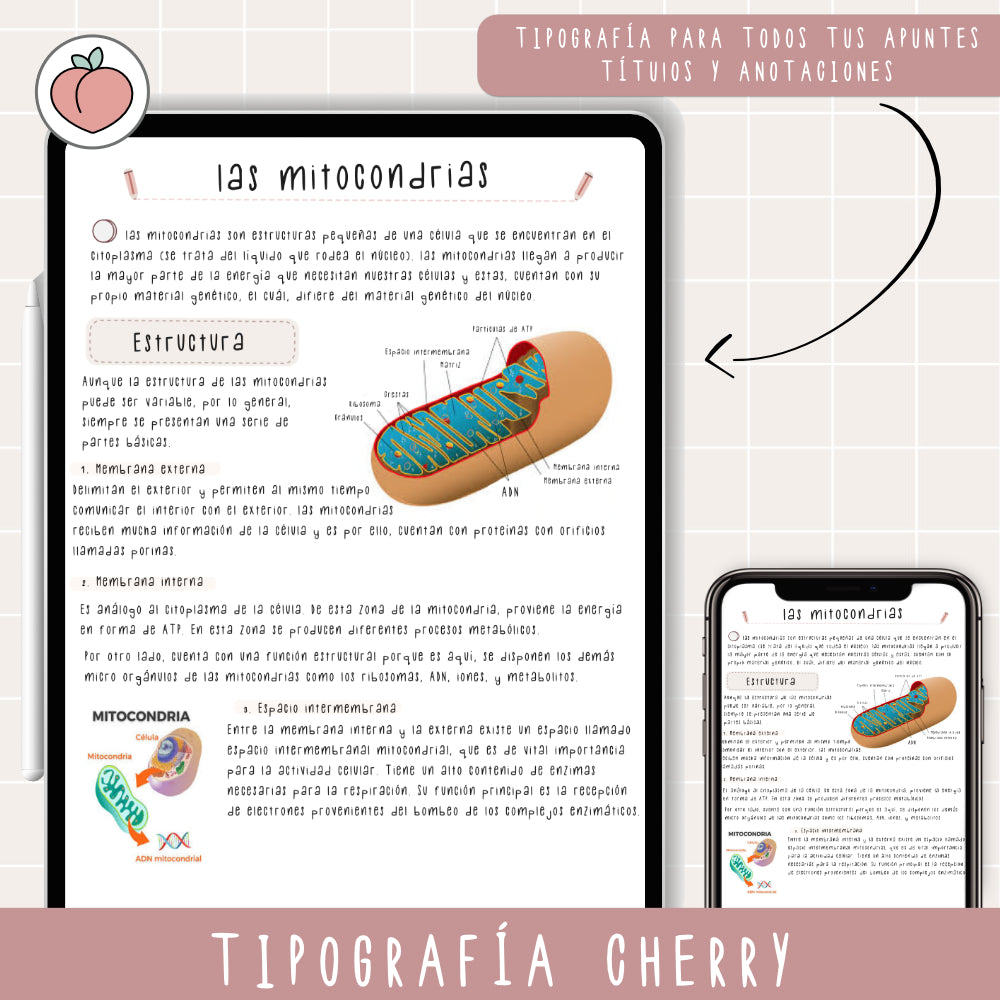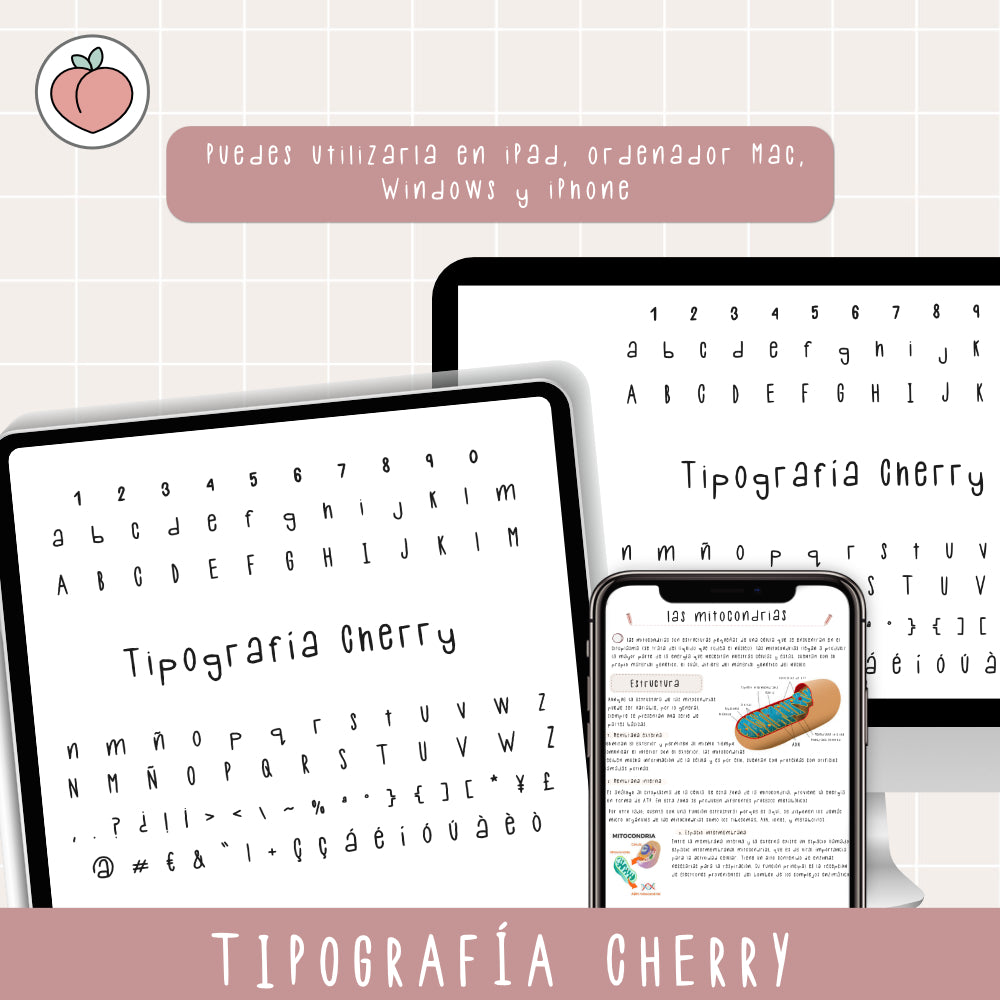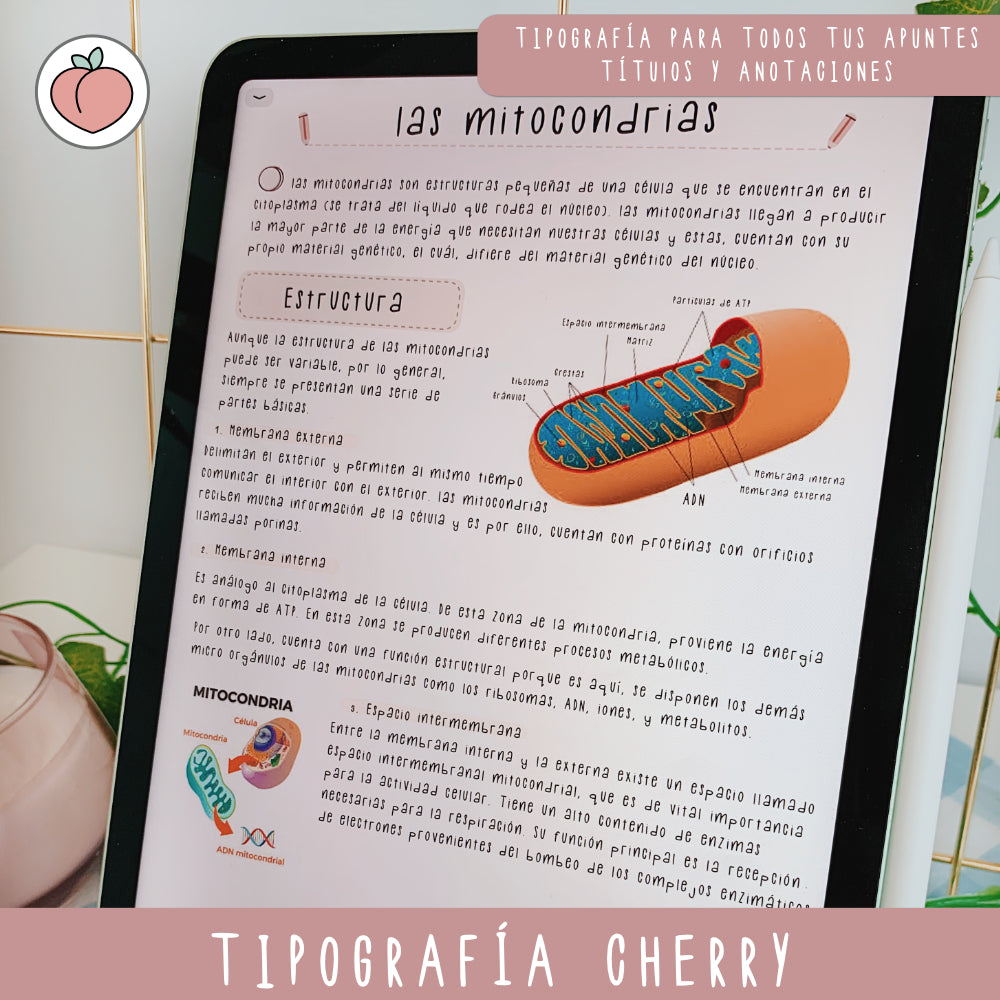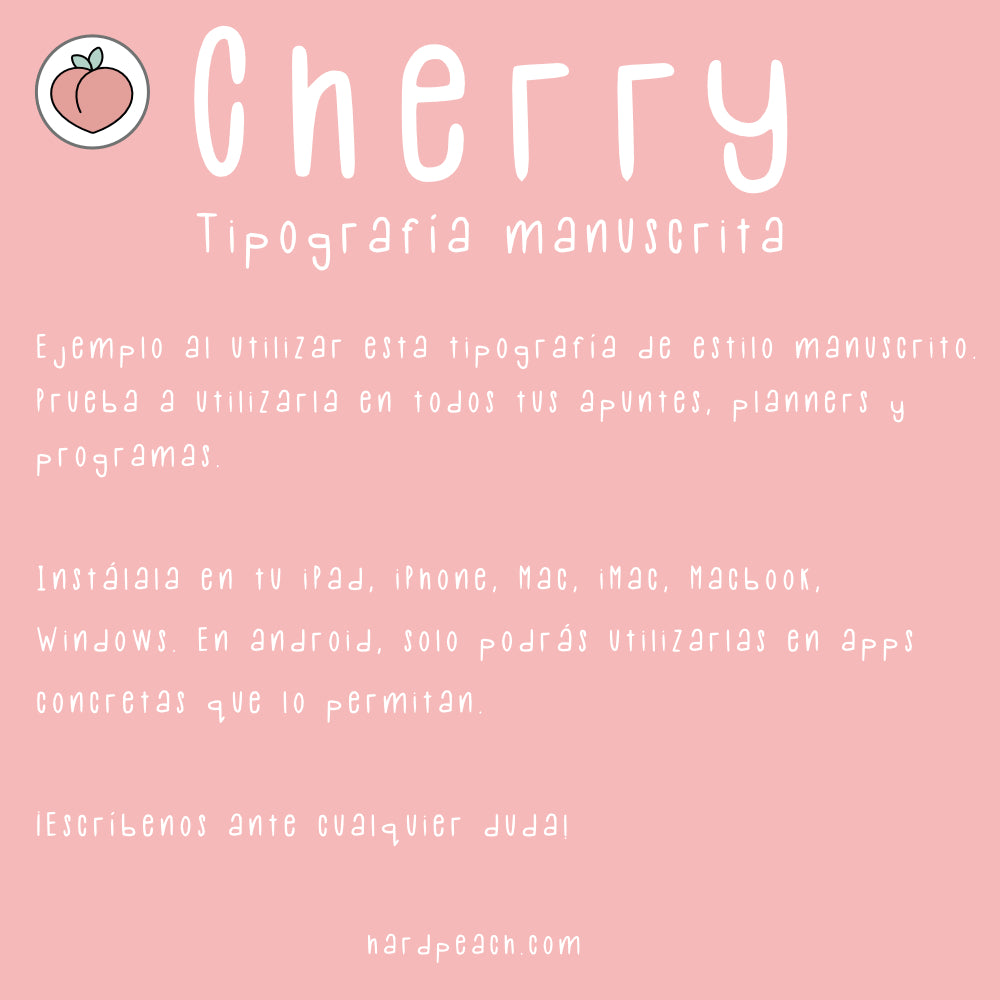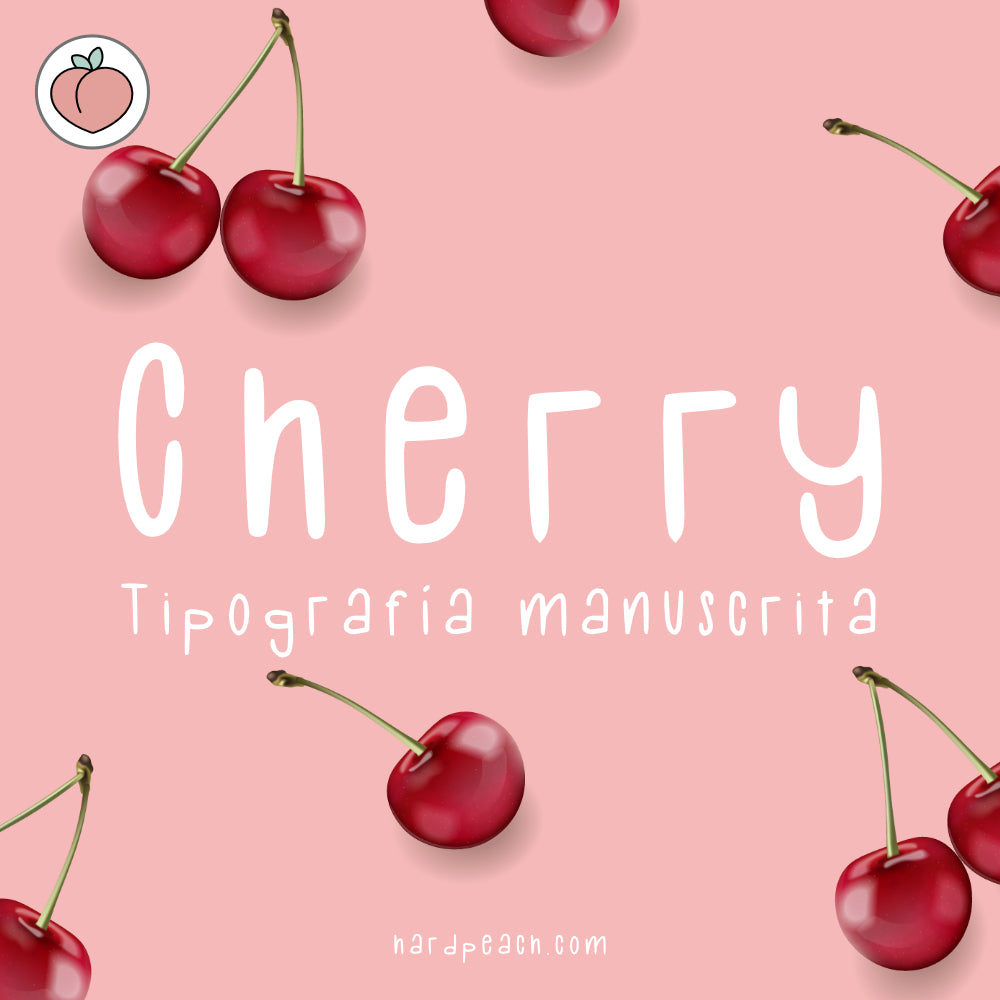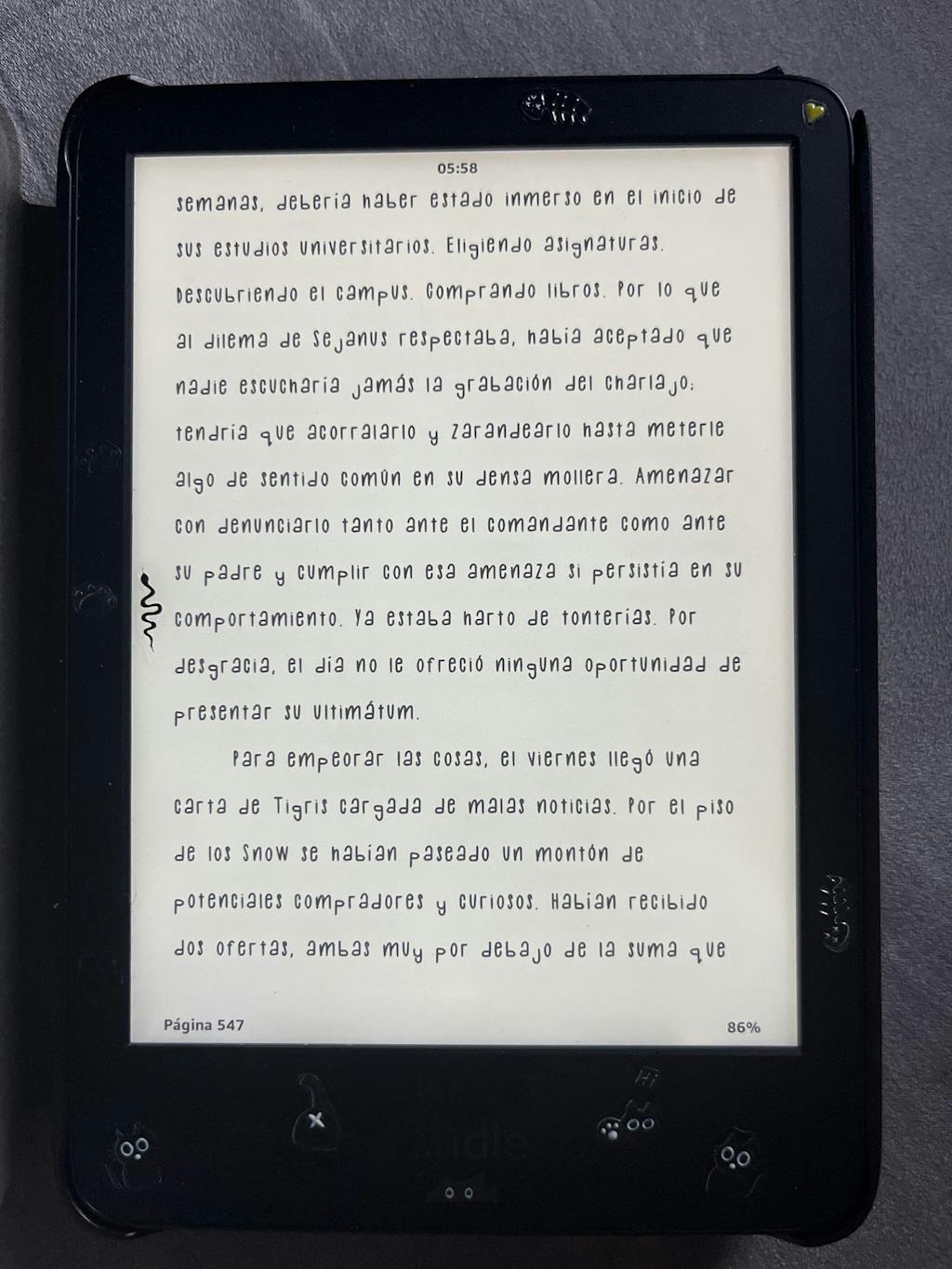
TIPOGRAFÍA MANUSCRITA CHERRY | FUENTE ESCRITA A MANO
Dale un toque personal y auténtico a tus apuntes, notas, títulos, esquemas y proyectos creativos con esta tipografía manuscrita Cherry, totalmente única.
Perfecta para quienes quieren destacar sus apuntes digitales, mejorar la presentación de sus notas o añadir un estilo especial a sus trabajos creativos. Su diseño versátil permite usarla en bullet journals, agendas, listas de tareas, diarios digitales, presentaciones, invitaciones, tarjetas, proyectos de diseño o cualquier creación que necesite un toque personal y manuscrito.
Esta tipografía aporta un estilo fresco, único y creativo, ideal para estudiantes, profesionales, diseñadores y cualquier persona que busque que su escritura digital refleje su personalidad y creatividad. Cada letra está cuidadosamente diseñada para que tu texto mantenga fluidez, elegancia y armonía visual, haciendo que cada palabra cobre vida y destaque sobre el resto.
Convierte tus apuntes y proyectos en algo especial, diferente y estéticamente atractivo, con un estilo manuscrito que combina modernidad y autenticidad, ideal para quienes buscan que sus textos no solo comuniquen, sino que también inspiran y enamoran a quien los lee.
La tipografía Cherry incluye todos los caracteres principales, mayúsculas, minúsculas, números, vocales con tildes (español), y acentuaciones abiertas (à) y signos. Además, incluye la acentuaciones y las letras ñ y ç.